Aspekte lebendiger Gestaltung
Gegen Ende des Seminars »Typografie intensiv« werden Aufgaben und eigene Ansprüche immer größer. Was intensiv erfahren und erprobt wurde wie Schriftwahl, Raster, Farbstimmung und Komposition fließen in den Projekten zusammen. Dabei sind die Arbeiten der einzelnen Teilnehmer sehr unterschiedlich. Jeder bringt eben auch seine eigene gestalterische »Biografie« mit. Diese Vielfalt wird angenommen, denn im Seminar wird nicht nach einem vorgefassten Gestaltungsbild unterrichtet.
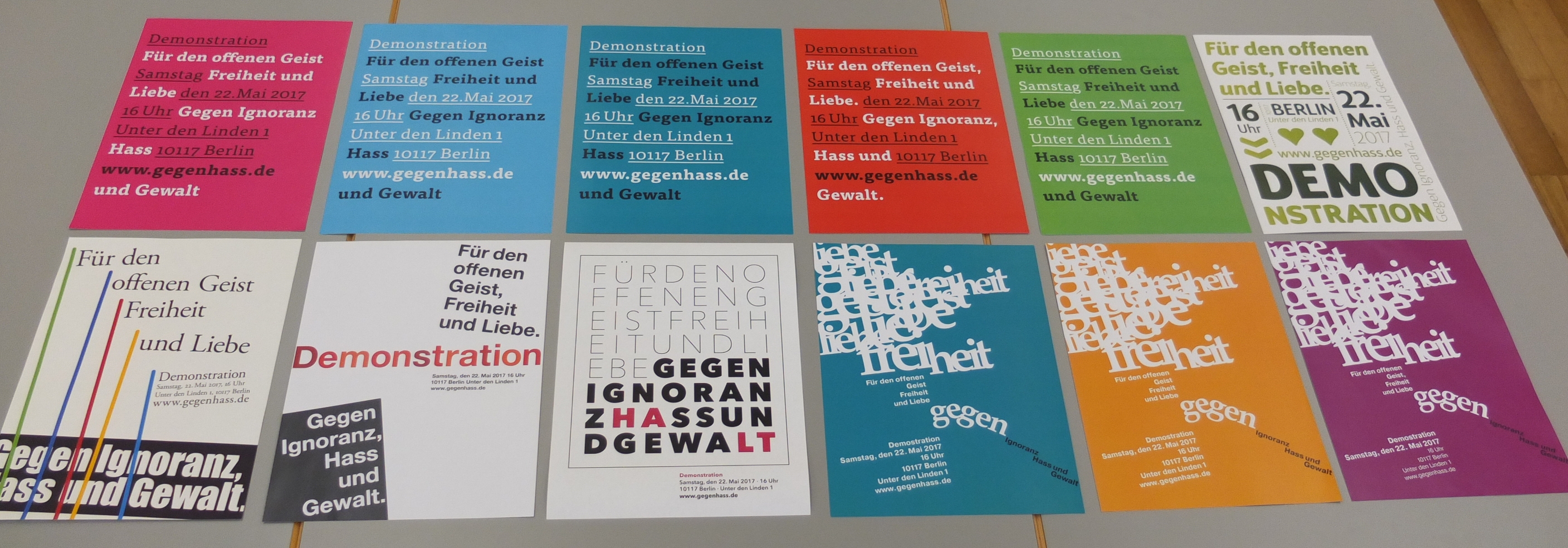
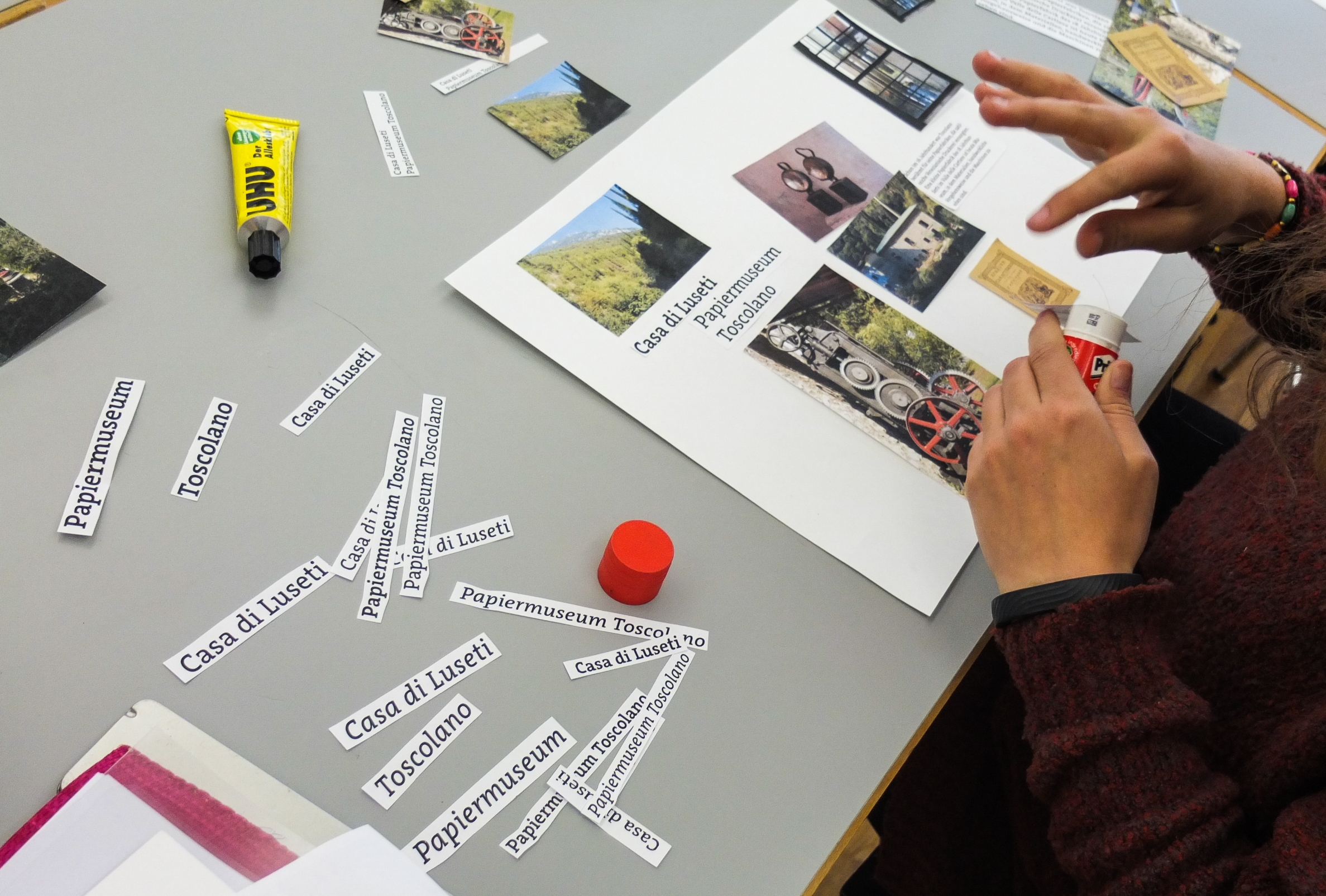
Deutlich zu sehen im Ergebnis für die Anzeige einer politischen Kampagne oder dem Plakat für die Fotografien Lyonel Feiningers, oder einer Seminarübung einer Bild-Text-Doppelseite (Casa di Luseti).
Für eine biografische Übung der Teilnehmerinnen lautete die Frage, wo pure Typografie aufhört und Infografik beginnt? Is es schon die Tabelle oder erst dann, wenn die Inhalte weitergehend visualisiert werden? Wie verständlich ist das Ganze und muß man sich nicht vor den heute recht beliebten hyperkomplizierten (und toll gestalteten), aber schwer lesbaren Infografiken hüten?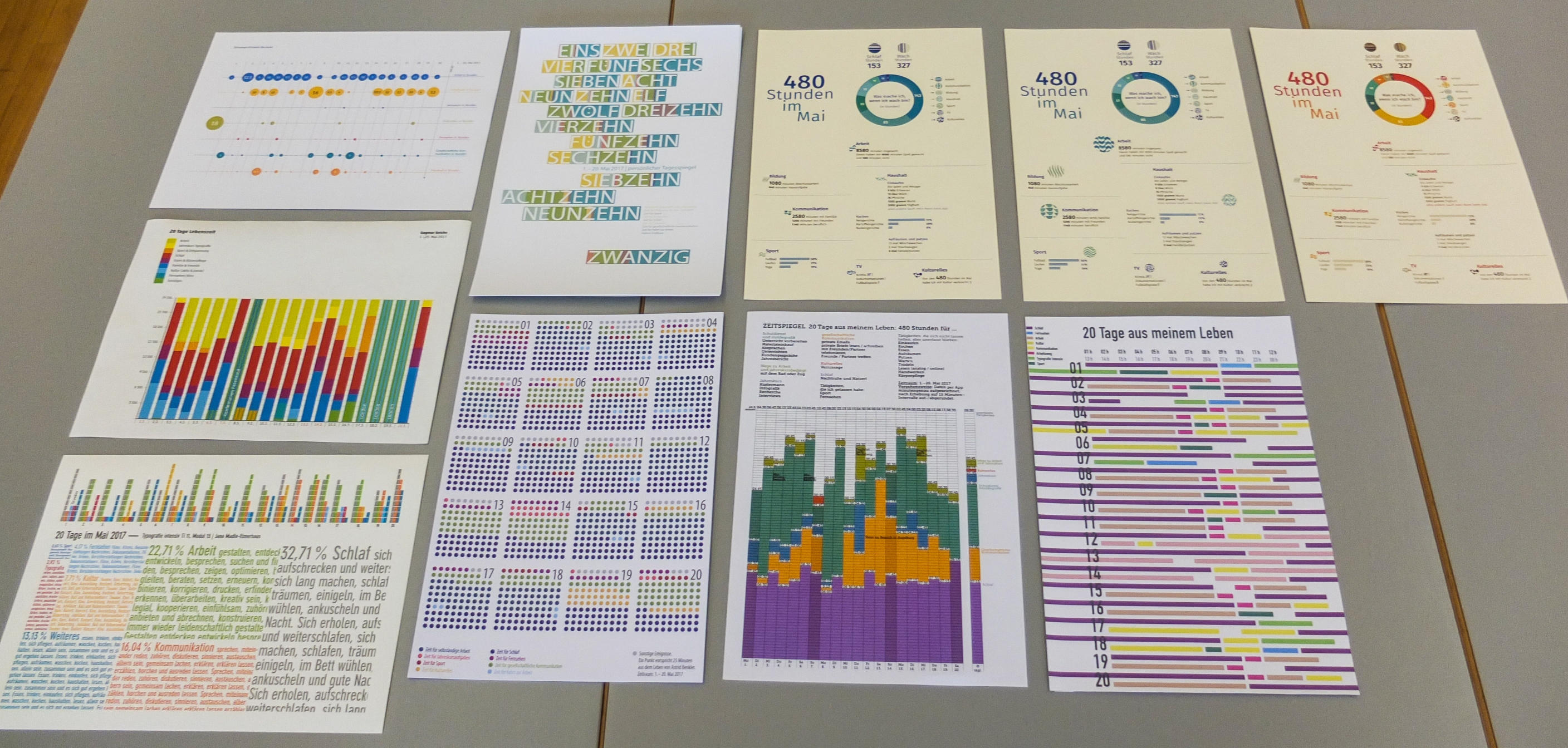
Gelassene, jedoch intensive Diskussionen der Teilnehmerinnen. Dagmar Nathalie Gorbach erklärt eine wichtige Übung, Rudolf Paulus Gorbach spricht über die Zusammenhänge von Bild und Gestaltung.
»Typografie intensiv« ist eine berufsbegleitende Fort- und Ausbildung für Typografie, Gestaltung und Design. Sie beginnt mit den Grundlagen wie Mikro- und Makrotypografie, Druckschriften, Basis der Gestaltung und Komposition, Farbe und Raster. Danach kommen zu gestaltende Projekte: Anzeige, Plakat, Flyer, Textbuch, Corporate Design, Infografik, Bild-Text-Buch, Website. Im Mittelpunkt dieser Design-Ausbildung steht die Typografie. Es endet mit einer kleinen theoretischen Studie zum Thema Typografie und verwandter Themen und einem Zertifikat der Typographischen Gesellschaft München e.V. Und – diese Ausbildung haben seit 1990 schon viele Teilnehmer erfolgreich beendet, die heute zum Teil an führenden Stellen in der Medienbranche arbeiten.